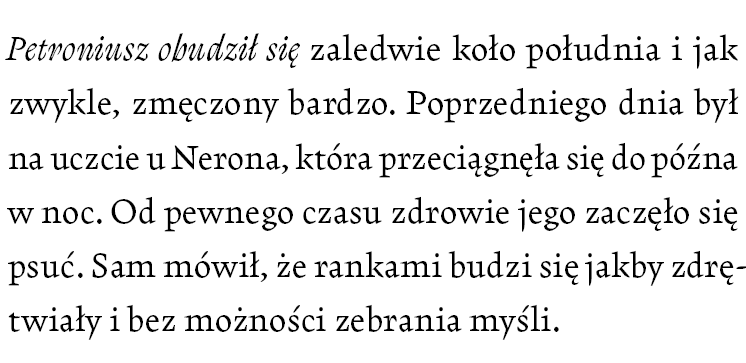
Skład tekstu krój Kristal
Krój Kri­stal (pro­jek­tant Eyal Holtzman)
1. Piękny i bar­dzo ele­gancki sze­ry­fowy krój pisma.
2. Posiada ponad­cza­sowy wygląd i świet­nie nadaje się do składu ksią­żek, ele­gnac­kich opra­co­wań, jak rów­nież jako krój do pro­jek­to­wa­nia okładek.
3. Posiada ostre zwień­cze­nia małych i wiel­kich liter, które bar­dzo oży­wiają akapit.
Spójrzmy na poniż­szy przykład: